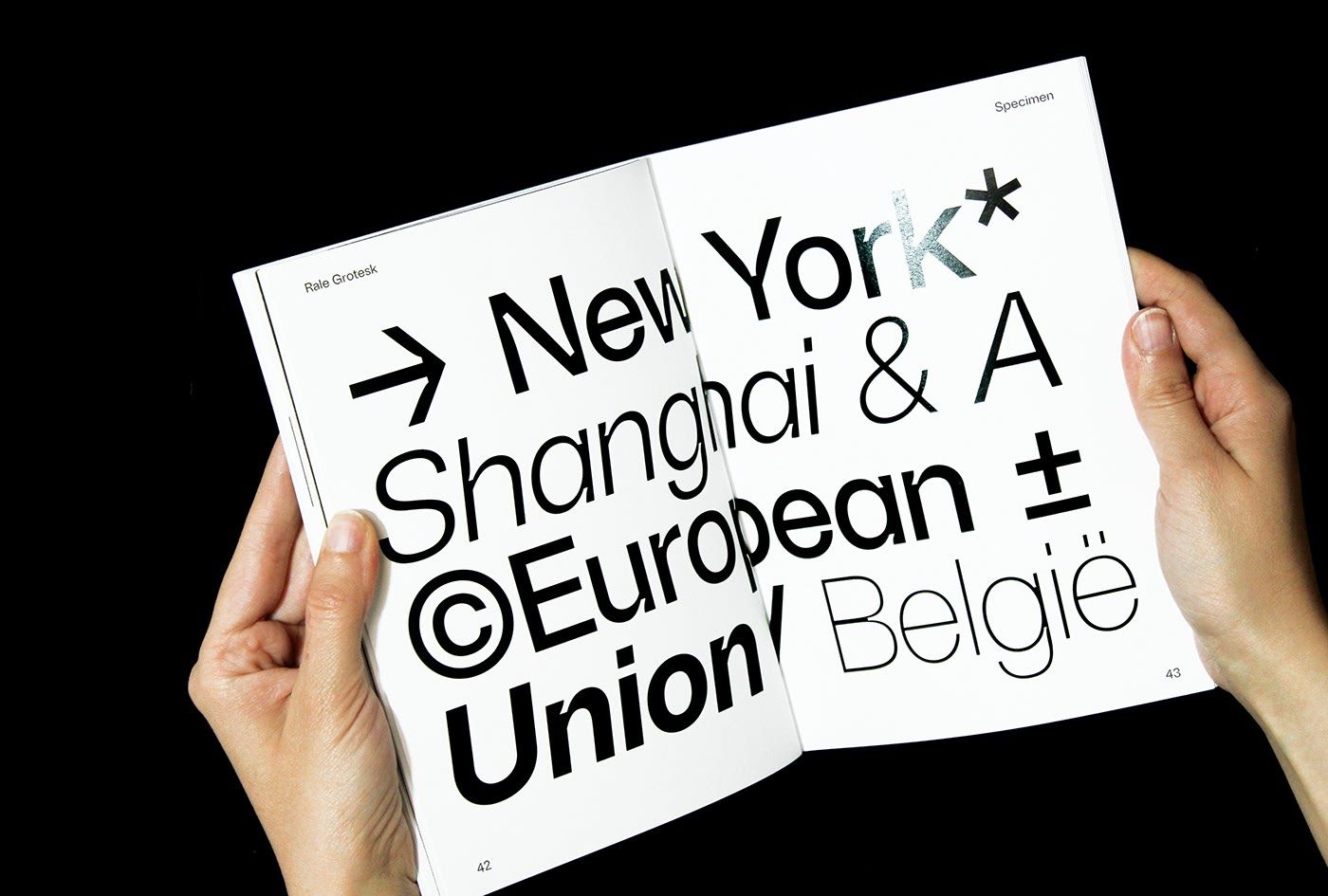
A szerb grafikus és művészeti vezető, Ognjen Gligorijevic gyönyörű betűcsaláddal rukkolt elő: íme, a Rale Grotesk!
Az utóbbi időszakban új tipográfiai szemléletmód nyert teret a mainstream grafika világában. A tintacsapda (ink trap) eltúlzása annak a folyamatnak a látványos kivetülése, melyben az eredeti szerepüket elvesztett elemek dekoratív funkciót kapnak. A tintacsapda eredetileg a betű azon része, mely a hagyományos nyomdai eljárások esetén a tinta felgyülemlését volt hivatott meggátolni a betű elemeinek kapcsolódásánál, ezáltal segítve a betű karakterének felismerhetőségét. Ez a feladat a tűpontos nyomdatechnológia megjelenésével elvesztette fontosságát, így most új életre kelve a tintacsapda dekorálja a már unalmasnak mondható groteszk betűket.
Ognjen egy kiadványban összesítette betűkészletét.